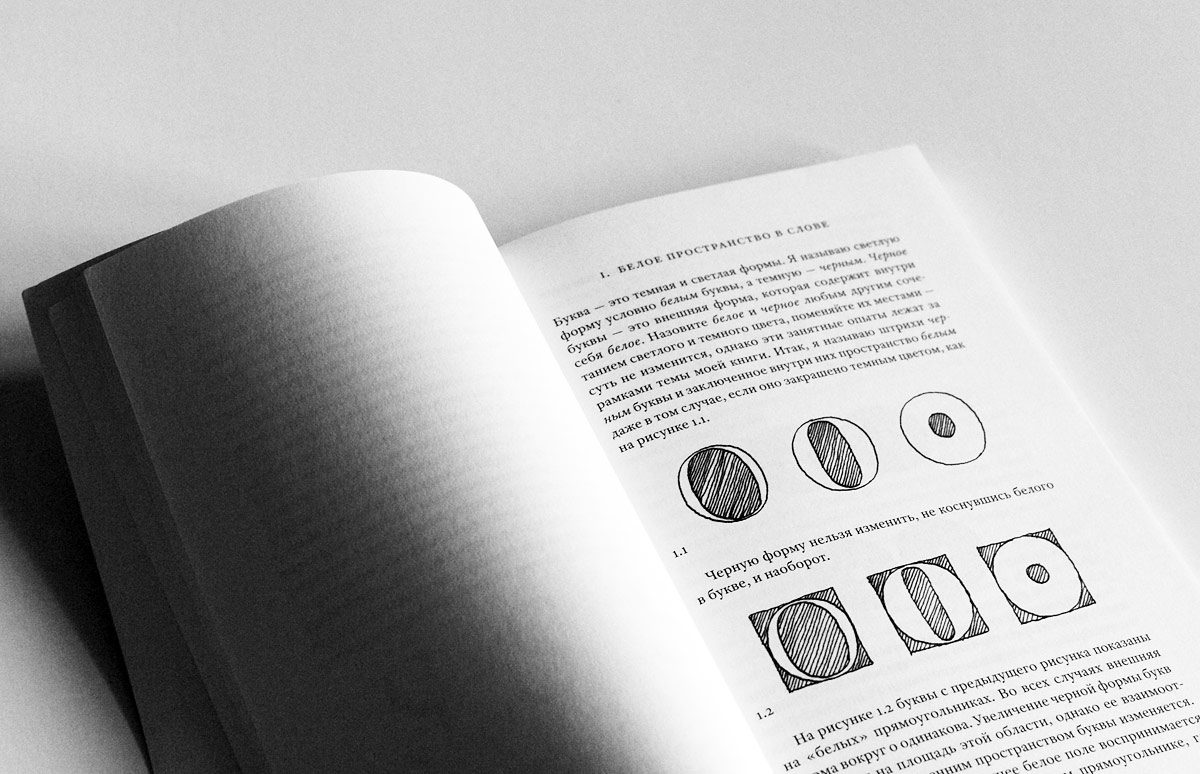
Штрих. Теория письма
Гер­рит Но­ор­дзей — вы­да­ю­щий­ся гол­ланд­ский шриф­то­вой ди­зай­нер, ти­по­граф, те­о­ре­тик и пе­да­гог. С 1960 по 1990 год ру­ко­во­дил кур­сом шриф­то­во­го ди­зай­на в Ко­ро­лев­ской ака­де­мии ис­кусств в Га­а­ге. В кни­ге «Штрих. Те­о­рия пись­ма» сум­ми­ро­ва­ны ре­зуль­та­ты прак­ти­че­ских за­ня­тий Но­ор­дзея и его уче­ни­ков в ака­де­мии. Зна­ме­ни­тая те­о­рия пись­ма охва­ты­ва­ет ряд важ­ных для шриф­то­во­го ди­зай­на по­сту­ла­тов — от по­ня­тия бе­ло­го про­стран­ства в сло­ве до по­дроб­но­го раз­бо­ра дви­же­ния штри­ха с ма­те­ма­ти­че­ской точ­ки зре­ния. Впер­вые опуб­ли­ко­ван­ная в 1985 го­ду в Ни­дер­лан­дах, кни­га бы­ла пе­ре­ра­бо­та­на ав­то­ром в 2005 го­ду и с тех пор пе­ре­ве­де­на на ан­глий­ский, фран­цуз­ский, ита­льян­ский, ис­пан­ский и дру­гие язы­ки. В 2013 го­ду кни­га вы­шла в пе­ре­во­де Ири­ны Смир­но­вой в из­да­тель­стве Дмит­рия Аро­но­ва. С его лю­без­но­го со­гла­сия мы пуб­ли­ку­ем фраг­мент из кни­ги — пер­вую гла­ву «Бе­лое про­стран­ство в сло­ве».
уква — это тём­ная и свет­лая фор­мы. Я на­зы­ваю свет­лую фор­му услов­но бе­лым бук­вы, а тём­ную — чёр­ным. Чёр­ное бук­вы — это внеш­няя фор­ма, ко­то­рая со­дер­жит вну­три се­бя бе­лое. На­зо­ви­те бе­лое и чёр­ное лю­бым дру­гим со­че­та­ни­ем свет­ло­го и тёмно­го цве­та, по­ме­няй­те их ме­ста­ми — суть не из­ме­нит­ся, од­на­ко эти за­нят­ные опы­ты ле­жат за рам­ка­ми те­мы мо­ей кни­ги. Итак, я на­зы­ваю штри­хи чёр­ным бук­вы и за­клю­чён­ное вну­три них про­стран­ство бе­лым да­же в том слу­чае, если оно за­кра­ше­но тём­ным цве­том, как на ри­сун­ке 1.1.
Ри­су­нок 1.1
Чёр­ную фор­му не­льзя из­ме­нить, не кос­нув­шись бе­ло­го в бук­ве, и на­о­бо­рот.
Ри­су­нок 1.2
На ри­сун­ке 1.2 бук­вы с пре­ды­ду­ще­го ри­сун­ка по­ка­за­ны на «бе­лых» пря­мо­уголь­ни­ках. Во всех слу­ча­ях внеш­няя фор­ма во­круг о оди­на­ко­ва. Уве­ли­че­ние чёр­ной фор­мы букв не вли­я­ет на пло­щадь этой об­ла­сти, од­на­ко её вза­и­мо­от­но­ше­ние с вну­трен­ним про­стран­ством бук­вы из­ме­ня­ет­ся. В тре­тьем при­ме­ре внеш­нее бе­лое по­ле вос­при­ни­ма­ет­ся го­раз­до силь­нее, не­же­ли в пер­вом пря­мо­уголь­ни­ке, где внеш­няя фор­ма по­дав­ле­на вну­ши­тель­ной пло­ща­дью вну­трен­не­го про­стран­ства бук­вы.
На прак­ти­ке мы ред­ко име­ем де­ло с од­ним зна­ком. Сло­во обыч­но со­став­ле­но из двух или не­сколь­ких со­сед­ству­ю­щих букв, что упрощён­но по­ка­за­но
на рисунке 1.3.
Ри­су­нок 1.3
Меж­бук­вен­ный про­бел в пер­вом и вто­ром слу­чае оди­на­ков, но во вто­рой па­ре он вы­гля­дит на­мно­го бóль­шим, так что бук­вы вос­при­ни­ма­ют­ся сто­я­щи­ми по­рознь. В по­след­ней стро­ке по­сле умень­ше­ния про­бе­ла бук­вы вновь вы­гля­дят как еди­ное це­лое. Сба­лан­си­ро­ван­ные бе­лые об­ла­сти су­ще­ствен­но ме­ня­ют де­ло. Бе­лое про­стран­ство в сло­ве — кра­е­уголь­ный ка­мень те­о­рии пись­ма.
От вза­и­мо­от­но­ше­ния фор­мы и контр­фор­мы (в те­о­рии пись­ма — чёр­но­го и бе­ло­го в сло­ве) за­ви­сит на­ше вос­при­я­тие объ­ек­тов. Так устро­е­ны ор­га­ны чувств, ко­то­рые пе­ре­да­ют сиг­на­лы моз­гу. Пись­мо с его стро­ги­ми пра­ви­ла­ми мо­жет быть удоб­ной мо­де­лью для изу­че­ния прин­ци­пов вос­при­я­тия, и вход в эту ла­бо­ра­то­рию от­крыт каж­до­му че­ло­ве­ку. Вез­де, ку­да бы ни упал наш взгляд, мы ста­но­вим­ся сви­де­те­ля­ми иг­ры тём­ных и свет­лых то­нов. Но ме­ня вол­ну­ет лишь слу­чай, ко­гда си­лы про­тив­ни­ков рав­ны, по­то­му что толь­ко так я мо­гу по­нять за­ко­ны, по ко­то­рым эта иг­ра свер­ша­ет­ся. Пред­по­ло­жим, что я уве­ли­чу пря­мо­уголь­ное по­ле на ри­сун­ке 1.2, по­сле че­го вну­трен­няя фор­ма зна­ка уже не бу­дет столь зна­чи­ма для ви­зу­аль­но­го вос­при­я­тия фо­на. Так и про­ис­хо­дит на ри­сун­ке 1.1, где внеш­ним по­лем для букв слу­жит книж­ная стра­ни­ца. Со­от­но­ше­ние чёр­но­го и бе­ло­го пе­ре­стаёт быть яв­ным.
Гер­рит Но­ор­дзей на за­ня­тии в Ко­ро­лев­ской ака­де­мии ис­кусств. Фо­то — Tânia Raposo.
Пе­ре­чис­лим ряд оче­вид­ных и зна­ко­мых нам со­от­но­ше­ний. Так, про­пор­ции ли­ста дик­ту­ют фор­му и рас­по­ло­же­ние тек­сто­вых бло­ков; сте­пень услов­ной чер­но­ты и дли­на на­бран­ной стро­ки вли­я­ют на меж­строч­ное рас­сто­я­ние; на­ко­нец, фор­мы букв вли­я­ют друг на дру­га, при­да­вая сло­вам тот или иной от­те­нок. Сло­ва, как от­дель­ные ато­мы, об­ра­зу­ют еди­ную плоть пись­ма. Рас­су­жде­ния о бук­ве или штри­хе не­воз­мож­ны без взгля­да на сло­во в це­лом. В сво­ей кни­ге я стрем­люсь разъ­ять сло­во на ча­сти с од­ной толь­ко це­лью — на­учить­ся его со­зда­вать.
Пись­мо осно­ва­но на со­от­но­ше­нии бе­лых форм вну­три сло­ва. Что­бы срав­нить яв­ле­ния меж­ду со­бой, все­гда тре­бу­ет­ся взгляд под опре­делён­ным уг­лом. Имен­но на бе­лое про­стран­ство в сло­ве сле­ду­ет опи­рать­ся, со­по­став­ляя все­воз­мож­ные ти­пы пись­ма с при­су­щи­ми им раз­лич­ны­ми кон­струк­ци­я­ми и штри­ха­ми. По­ня­тие бе­ло­го в сло­ве рав­но при­ме­ни­мо к ру­ко­пис­но­му шриф­ту и к ти­по­гра­фи­ке, к ис­то­ри­че­ско­му и со­вре­мен­но­му пись­му, к за­пад­но­му пись­му и к пись­му дру­гих куль­тур, про­ще го­во­ря — оно объ­ем­лет пись­мо как еди­ное яв­ле­ние.
Ис­сле­до­ва­ния на­ших дней об­ра­ще­ны в боль­шей сте­пе­ни к чёр­ной фор­ме бук­вы, но не к бе­ло­му вну­три сло­ва, и, как след­ствие, они ис­чер­пы­ва­ют­ся рас­смот­ре­ни­ем по­верх­ност­ных раз­ли­чий. Уни­вер­саль­ный спо­соб срав­не­ния ру­ко­пис­но­го шриф­та и ти­по­граф­ских ли­тер кро­ет­ся от­нюдь не в услов­ном чёр­ном бук­вы. Чёр­ные фор­мы ти­по­граф­ской ли­те­ры и на­пи­сан­ной бук­вы на­столь­ко раз­лич­ны, что по­пыт­ки всерьёз срав­ни­вать их об­ре­че­ны на про­вал. По­сколь­ку в об­ласть ин­те­ре­сов ти­по­гра­фи­ки по­па­да­ют толь­ко чёр­ные фор­мы букв, из­го­тов­лен­ных для пе­ча­ти на бу­ма­ге, ака­де­ми­че­ское изу­че­ние пись­ма вы­ну­жде­но раз­де­лять ру­ко­пис­ный шрифт и ис­то­рию на­бор­но­го шриф­та. Наш под­ход ис­клю­ча­ет по­доб­ное раз­гра­ни­че­ние. Раз­бор ис­то­ри­че­ско­го пись­ма — если су­дить по кни­гам — за­мы­ка­ет­ся на во­про­сах па­лео­гра­фии или же ди­пло­ма­тии, ко­то­рая изу­ча­ет пись­мо по ар­хив­ным до­ку­мен­там и пись­мам, а так­же эпи­гра­фи­ки, ис­сле­ду­ю­щей древ­ние мо­ну­мен­таль­ные над­пи­си. Со­вре­мен­ное пись­мо пол­но­стью остав­ле­но без вни­ма­ния. Се­го­дня оно в ру­ках пе­да­го­гов, ко­то­рые без­рас­суд­но под­вер­га­ют опас­но­сти всю ци­ви­ли­за­цию. Воз­мож­но, я пре­уве­ли­чи­ваю, но раз­ве за­пад­ный ци­ви­ли­зо­ван­ный мир не пред­став­ля­ет со­бой куль­тур­ное со­об­ще­ство, не­мыс­ли­мое без пись­мен­но­сти? Пе­да­го­ги чуть ли не гор­дят­ся тем, что осво­бо­жда­ют де­тей от изу­че­ния основ пись­ма, но тем са­мым они под­ры­ва­ют устои за­пад­ной ци­ви­ли­за­ции. Устра­ша­ю­щий рост бес­куль­ту­рья свя­зан с пре­не­бре­же­ни­ем к уро­кам пись­ма в шко­лах.
Ко все­му про­че­му, де­ло ухуд­ша­ет раз­гра­ни­че­ние на­ук о пись­ме. Точ­ка зре­ния, что пись­мо есть чёр­ные фор­мы букв, толь­ко под­тал­ки­ва­ет учё­ных к это­му. Сре­ди ря­да обо­соб­лен­ных на­ук нет ме­ста со­вре­мен­но­му пись­му, по­сколь­ку его чёр­ные стро­ки не име­ют ни­че­го об­ще­го с чёр­ны­ми фор­ма­ми пись­мен, ко­то­рые пы­та­ют­ся по­стичь па­лео­гра­фы. Я не пре­уве­ли­чу, если ска­жу, что школь­ный учи­тель за­кры­ва­ет гла­за на пло­хой по­черк, по­то­му что счи­та­ет хо­ро­шее пись­мо «на­ри­со­ван­ным», в то вре­мя как оно долж­но быть «на­пи­сан­ным». За­тро­ну­тое вы­ше раз­гра­ни­че­ние дис­ци­плин толь­ко под­креп­ля­ет эту точ­ку зре­ния. Не будь её, пе­да­го­гам при­шлось бы со­по­став­лять соб­ствен­ный по­черк с при­ме­ра­ми хо­ро­ше­го пись­ма, а та­кое срав­не­ние ока­жет­ся для них не­вы­год­ным. Сей­час же они спо­кой­но мо­гут иг­но­ри­ро­вать до­стой­ные об­раз­цы пись­ма, по­сколь­ку оно от­но­сит­ся к дру­гой дис­ци­пли­не и его пре­по­да­ва­ние не вхо­дит в круг их за­дач.
По­доб­ным же об­ра­зом оправ­ды­ва­ет­ся ака­де­ми­че­ская сре­да. Пред­по­ло­жить, что на­бор­ный шрифт и пись­мо род­ствен­ны, про­сто не­воз­мож­но, по­сколь­ку эта мысль идёт враз­рез с устой­чи­вы­ми пре­ду­бе­жде­ни­я­ми учё­ных му­жей (а пред­рас­су­док тем и от­ли­ча­ет­ся, что его не­воз­мож­но под­верг­нуть со­мне­нию). Ко­гда фак­ты на­тал­ки­ва­ют нас на идею срав­не­ния на­бор­но­го шриф­та и ру­ко­пис­но­го пись­ма, их пы­та­ют­ся скрыть. Хо­ро­ший при­мер на этот счёт — ис­то­рия ко­ро­лев­ской ан­ти­к­вы (Romain de Roi). Она бы­ла на­ре­за­на око­ло 1700 го­да по ука­за­нию ко­ро­лев­ской ко­мис­сии по стан­дар­ти­за­ции на­ук и ремё­сел. Про­ект раз­ра­ба­ты­вал­ся по мо­дуль­ной сет­ке — тра­ди­ци­он­ным для то­го вре­ме­ни спо­со­бом мас­шта­би­ро­ва­ния ри­сун­ков.